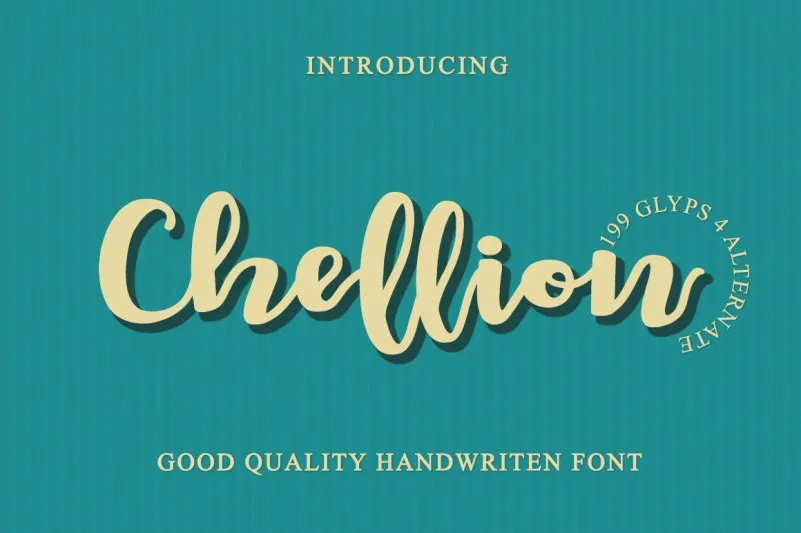
Chellion Script Font – Download Grátis
A Chellion é uma fonte escrita a mão que oferece tanto um toque inteligente quanto divertido. Ideal para quem busca algo que traga diversão sem sacrificar qualidade, ela traz consigo uma série de surpresas e pode transformar qualquer projeto manufatureiro em uma obra capaz de chamar atenção imediatamente. Seja um cartaz inspirador ou uma etiqueta repleta de personalidade, a Chellion é perfeita para aqueles que valorizam tanto o cuidado quanto o brilho de uma letra escrita à mão, mas querem manter todo seu poder e estilo na medida certa. Para designers, amantes da arte ou quem simplesmente busca um pouco de diversão no trabalho, a Chellion é uma escolha imbatível para complementar qualquer projeto visual.